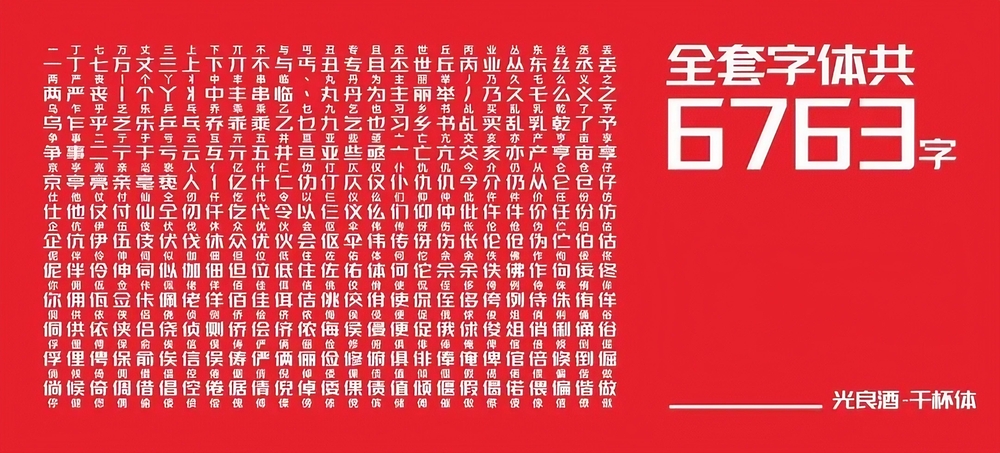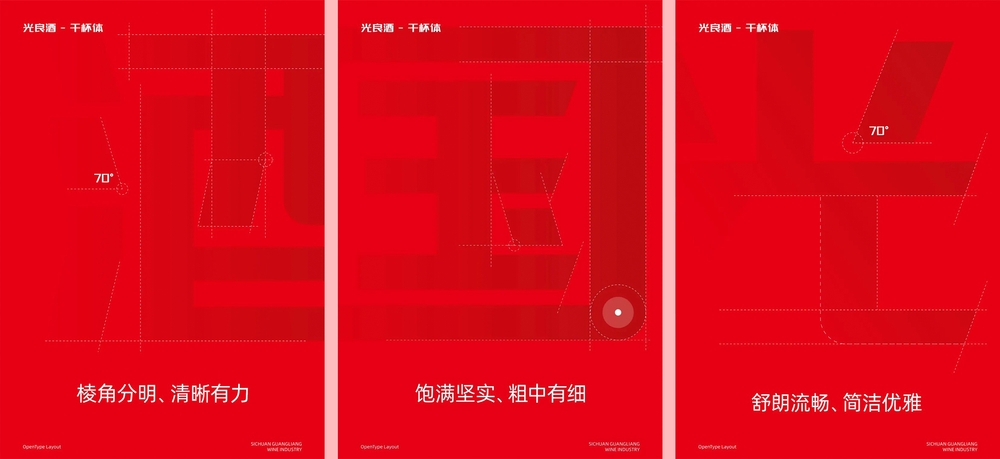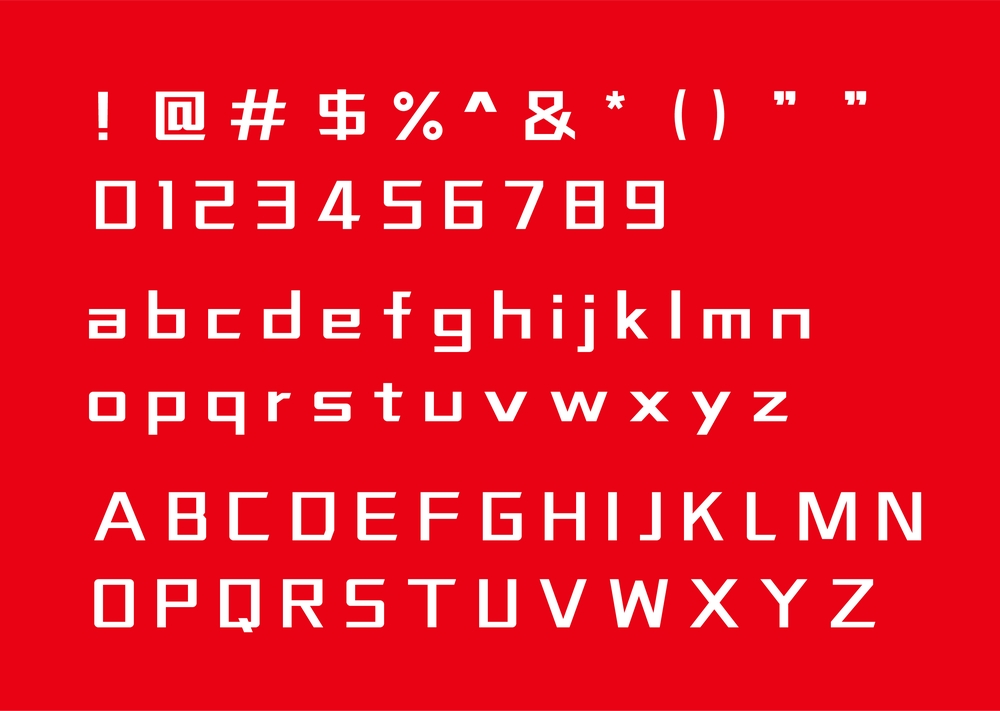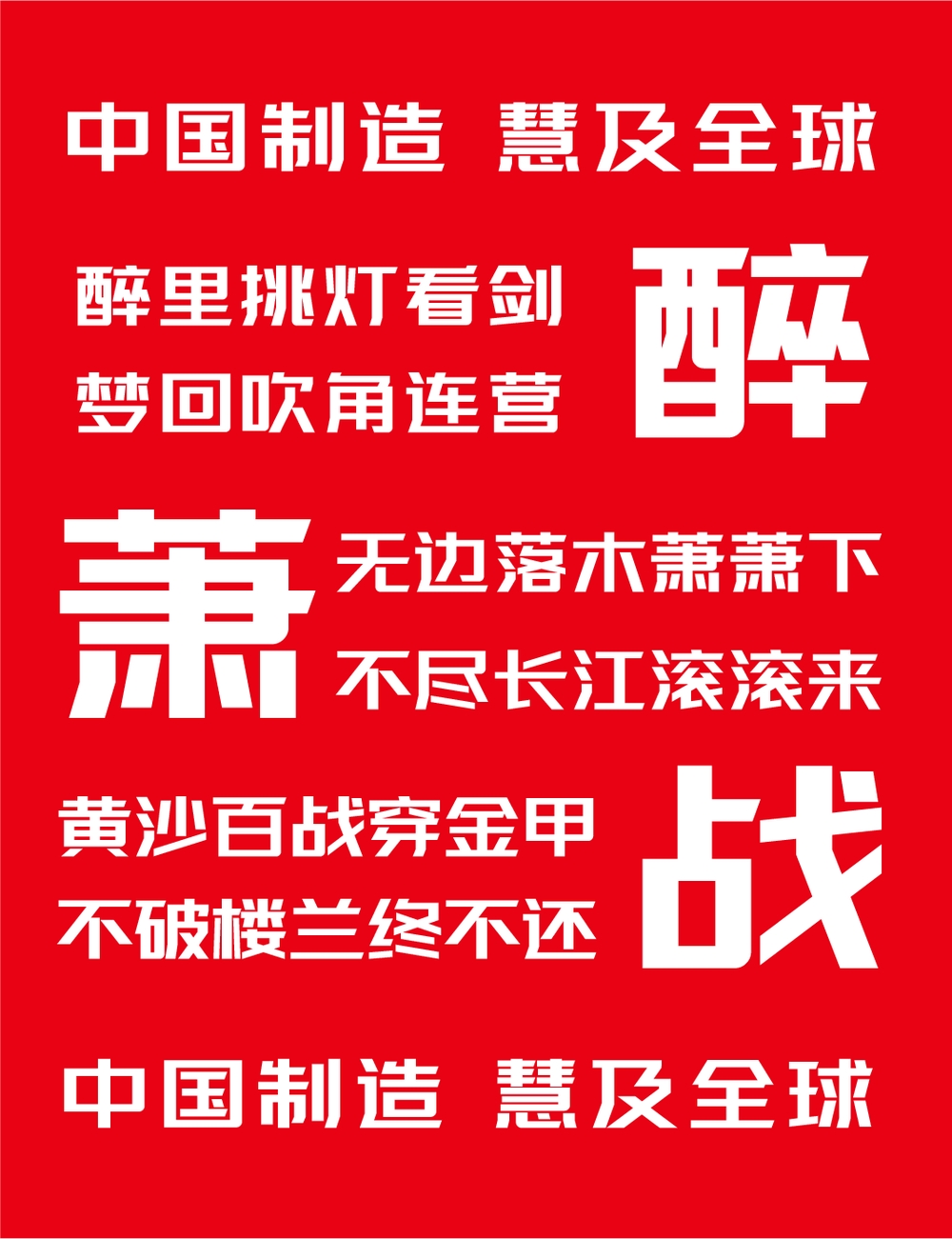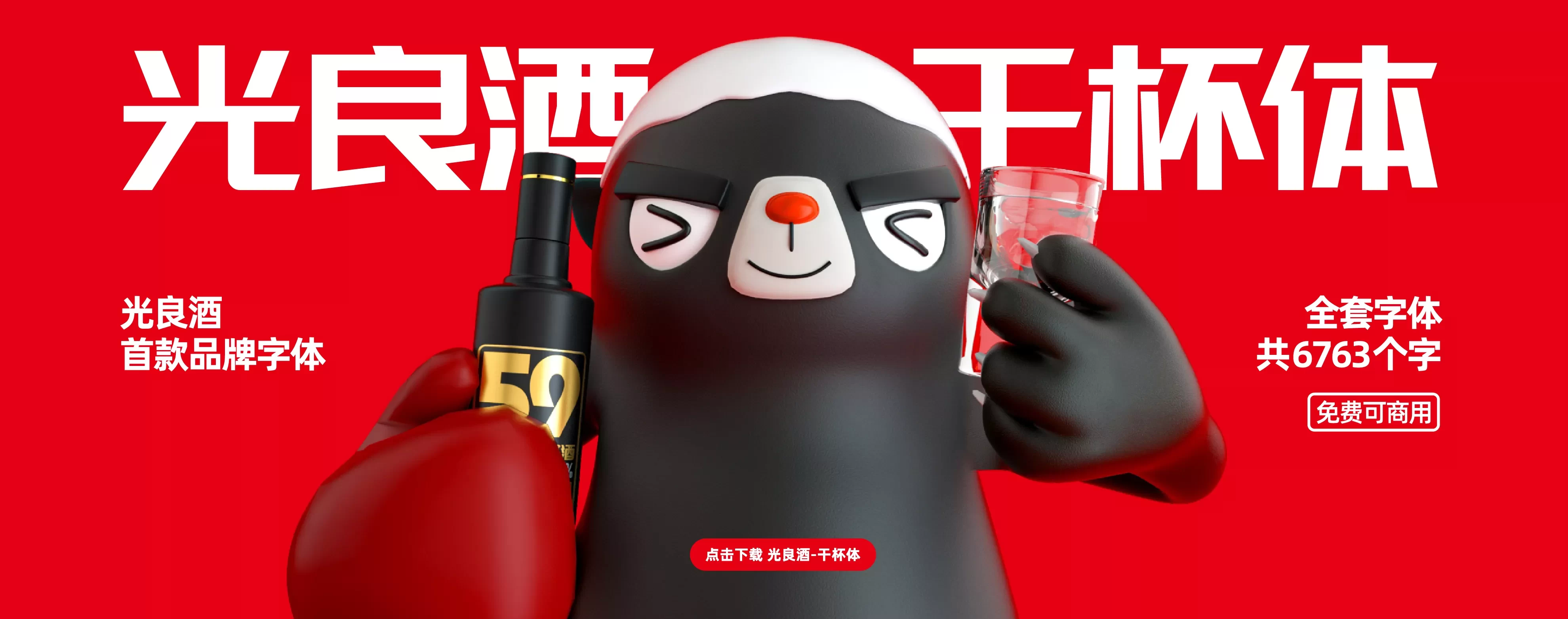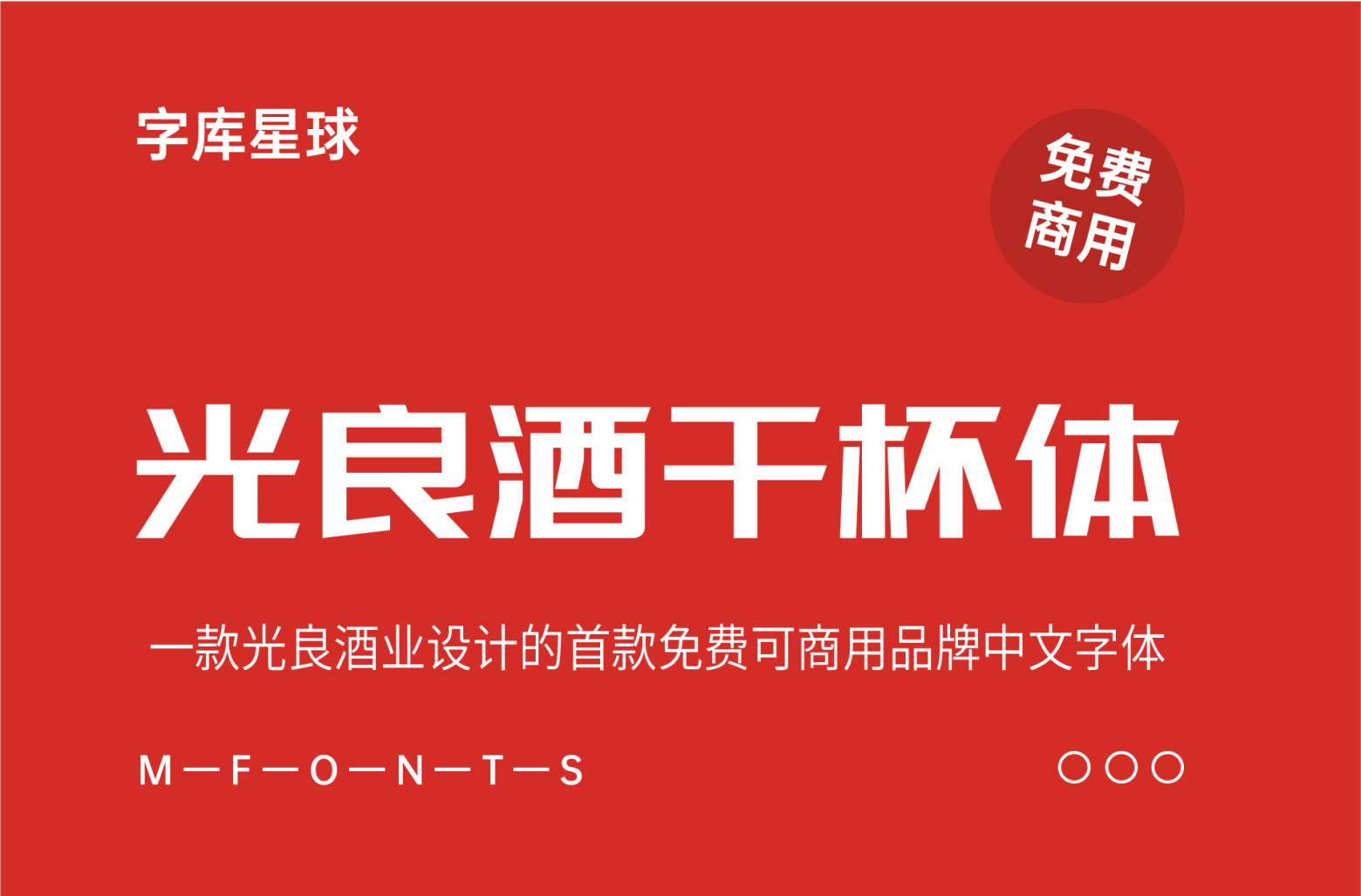
去年3月,光良企业决定做一款自己的字体,联系了全网第一的资深字体设计师刘兵克及其创办的“字体江湖”团队,用了大半年时间,研发了品牌字体【光良酒-干杯体】。同时也是业内首个推出开源字体的白酒品牌,在经历过字体使用上的困扰后,决心联合专业机构研发设计。便于光良以及整个白酒行业的所有同仁突破桎梏,放心使用。
这套字体总共有 6763 个常用字,此外,结合白酒行业同仁的高频使用场景,我们还设计了 55 个不同的“酒”字标识,以及原料、香型、货运相关的数十个标识,希望能为酒业同仁们的传播使用提供方便。
字体特征
「光良酒-干杯体」是光良酒首款免费商用品牌字体,设计师采用现代化的设计思路,在整体视觉上体现出舒朗流畅、简洁优雅;字型笔画中一撇一捺,清晰有力,棱角之间,尽显态度。